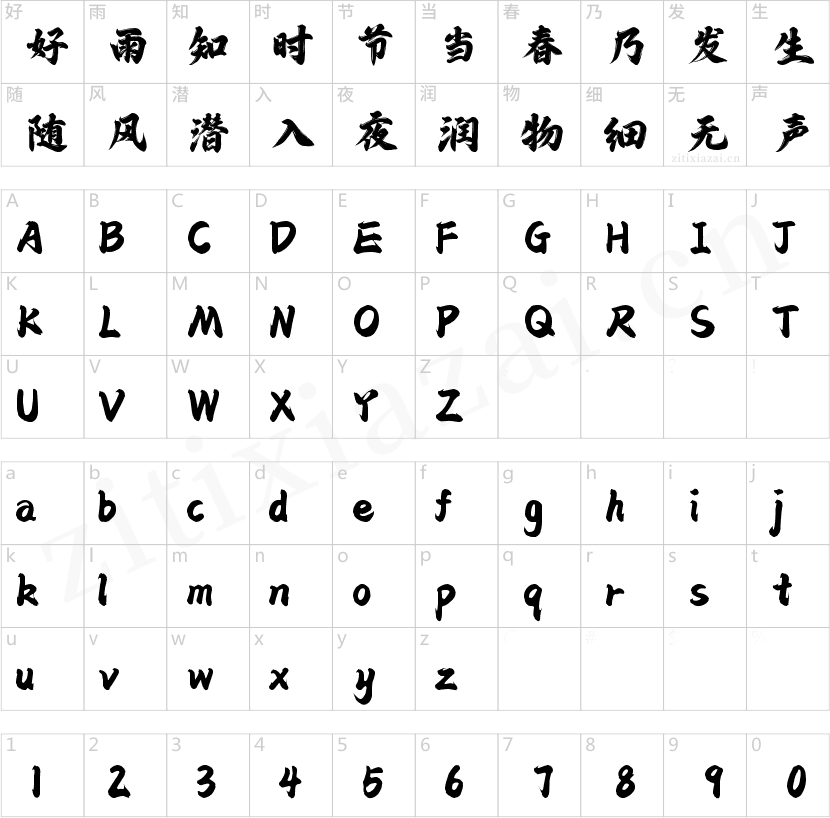
字魂龙腾楷书
字魂龙腾楷书,这款字体结构工整、笔画清晰,兼顾美观与易读性,适用于标题、正文、海报、包装、LOGO 等多种场景。字形优雅稳定,风格百搭耐看,适配日常排版与创意设计,让文字呈现更舒适、更具质感。字魂龙腾楷书一笔一画,皆是细节,以均衡的比例、流畅的线条打造舒适视觉体验,字形端正大气,风格简约现代。无论是商业设计、品牌宣传还是日常排版,都能轻松驾驭,让文字更有格调与力量。字魂龙腾楷书字体下载。